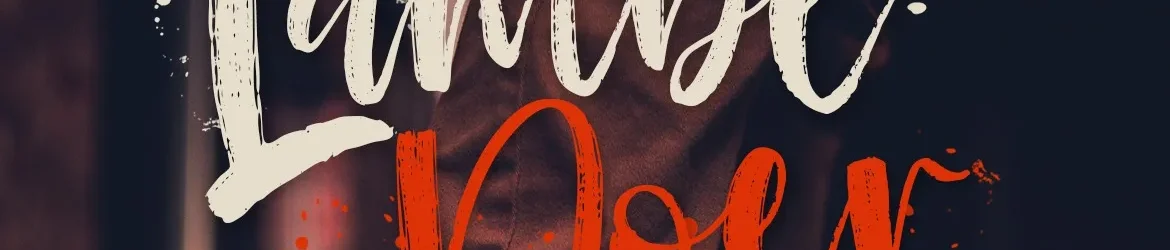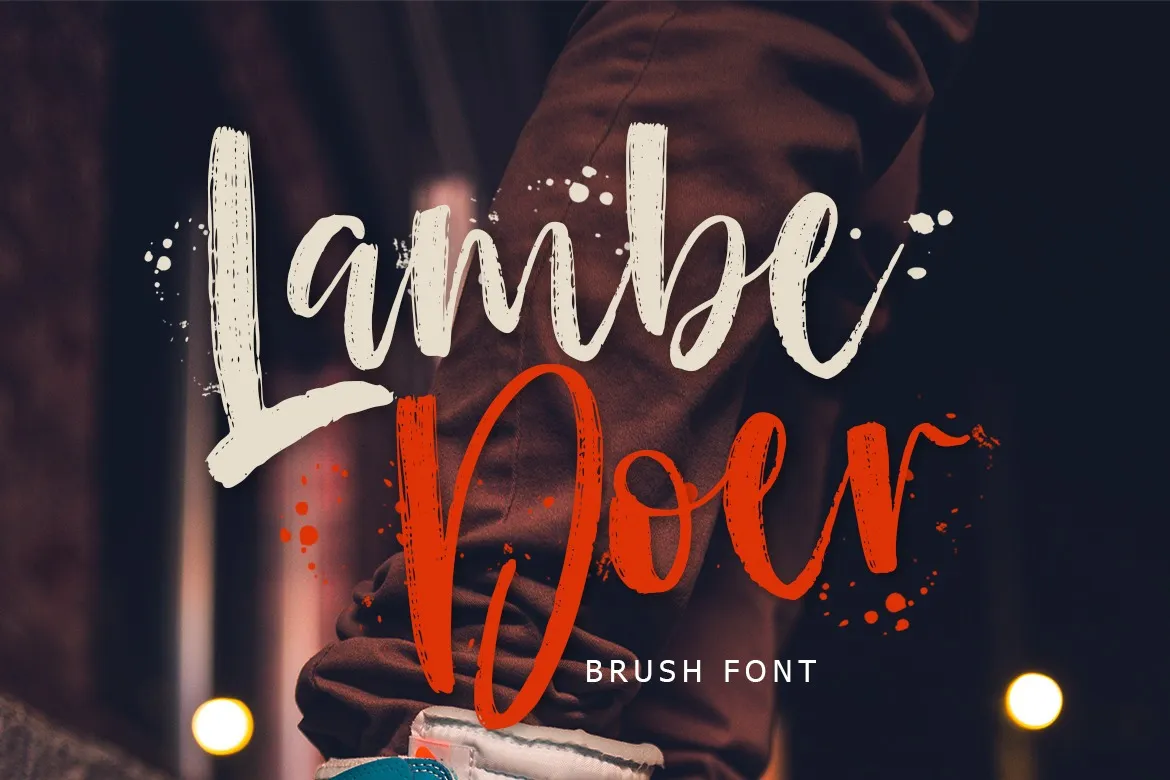
Lambe Doer Font – Fonte Grátis
Lambe Doer Font
A Lambe Doer Font é uma elegante tipografia casual criada pelo designer lyanatha. Com seu traço suave e script moderno, ela pode revigorizar qualquer projeto editorial ou design web com um toque sofisticado. Perfeita para criar textos profissionais que transmitem luxo e simplicidade contemporânea, a Lambe Doer é uma opção perfeita para designers buscando uma fonte casual mas moderna que não deixa nada à desejar em elegância. Ideal tanto para sites quanto para revistas e anúncios, a Lambe Doer oferece o contraste perfeito entre rusticidade e sofisticação, tornando-a um recurso indispensável para designers atentos aos detalhes.